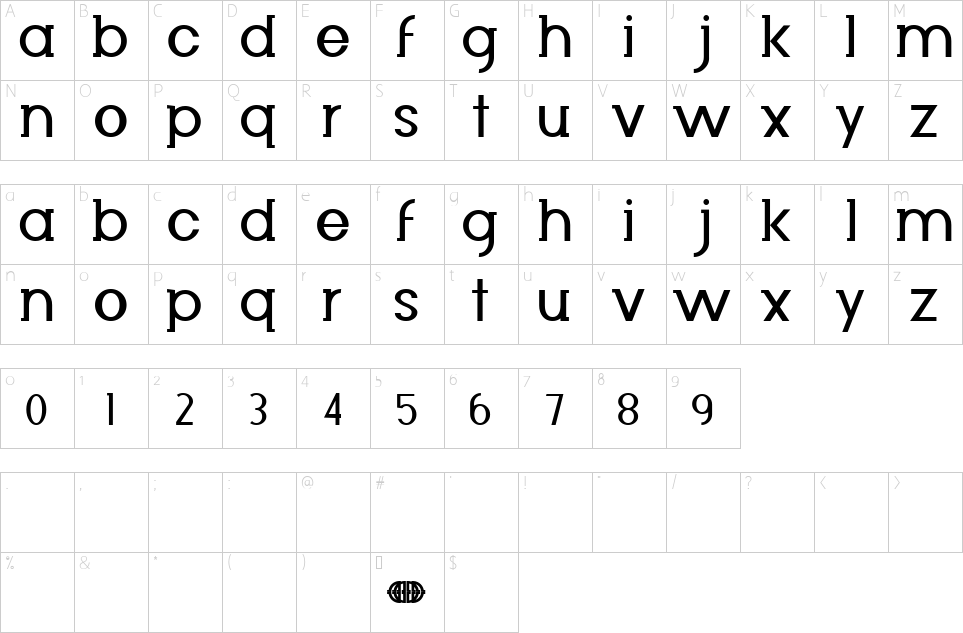
Diminuto é uma elegante fonte escolar que combina uma delicada feminilidade com simplicidade pura, perfeitamente adequada para projetos digitais de pequeno porte ou conteúdo educacional. Desenvolvida por MuraKnockout Media & Design, esta fonte foi criada especialmente para quem procura uma opção clara e limpa que se destaca em qualquer layout. Com seu design clean e minimalista, Diminuto é perfeito para títulos de página, listas e textos menores, oferecendo um visual moderno sem comprometer a leitura. Sucesso na categoria de fontes gratuitas, Diminuto já foi baixada mais de 10 mil vezes, uma indicação do seu valor para projetos que buscam simplicidade e elegância. Baixe agora sua cópia e encontre o equilíbrio perfeito entre sofisticação e minimalismo na fonte Diminuto.